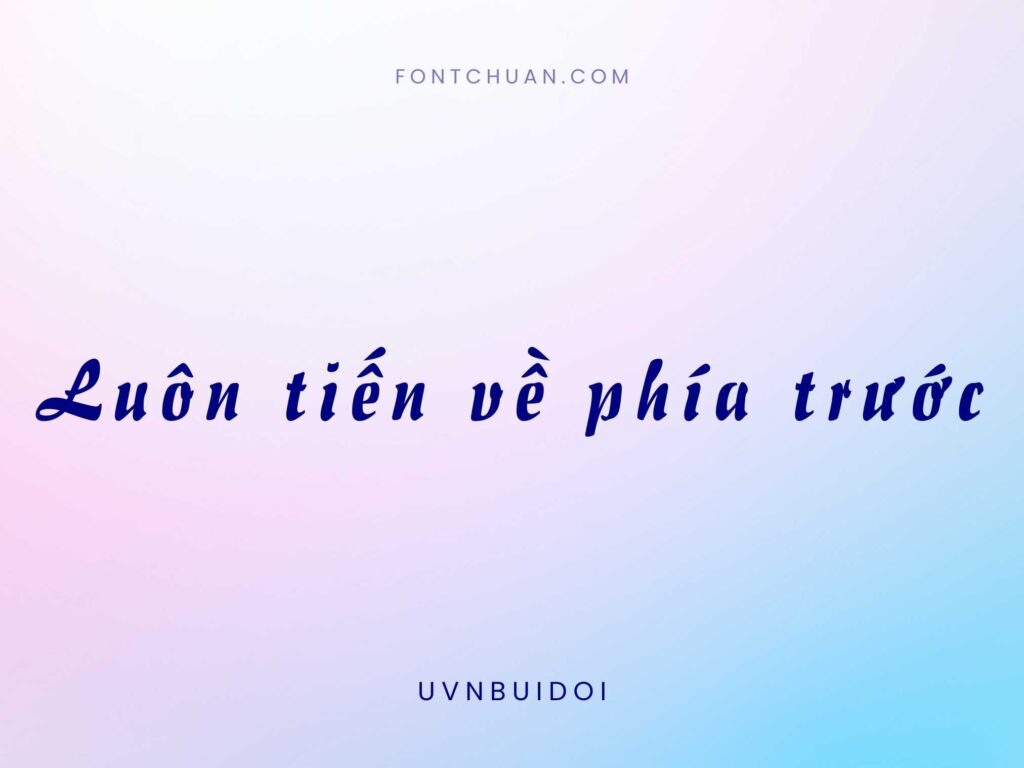
Font UVN Bui Doi Việt Hóa
UVN Bụi Đời là một phông chữ script đậm nét, mang phong cách thư pháp với các đường nét uyển chuyển và mạnh mẽ. Được thiết kế bởi Tom Trương vào năm 2001, phông chữ này tạo cảm giác nghệ thuật và cá tính, phù hợp cho các thiết kế cần sự độc đáo và sáng tạo. UVN Bụi Đời hỗ trợ đầy đủ các ký tự tiếng Việt, giúp người dùng dễ dàng sử dụng trong các dự án sáng tạo liên quan đến văn hóa Việt Nam.
Với thiết kế độc đáo và nghệ thuật, UVN Bụi Đời phù hợp cho các ứng dụng như thiệp mời, tiêu đề sách, thiết kế logo và các ấn phẩm nghệ thuật. Trong lĩnh vực sự kiện, phông chữ này có thể được sử dụng trong các dịp như lễ hội, lễ cưới và các sự kiện văn hóa. Ngoài ra, UVN Bụi Đời còn là một Font chữ ảnh cưới lý tưởng, giúp trang trí thiệp cưới, album ảnh hoặc các sản phẩm kỷ niệm, mang đến sự tinh tế, lãng mạn và sang trọng cho các thiết kế. Font này cũng phù hợp với các ngành nghề như thiết kế đồ họa, nghệ thuật trang trí và xuất bản.